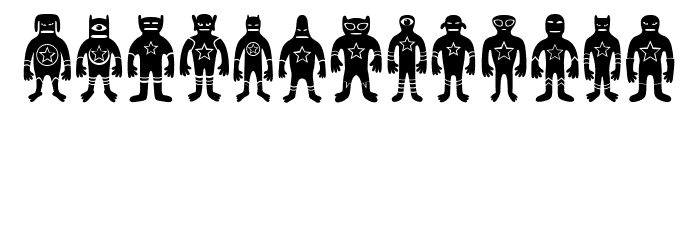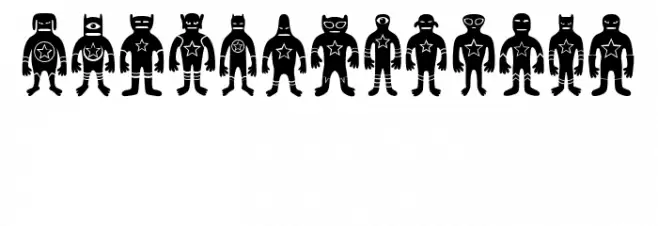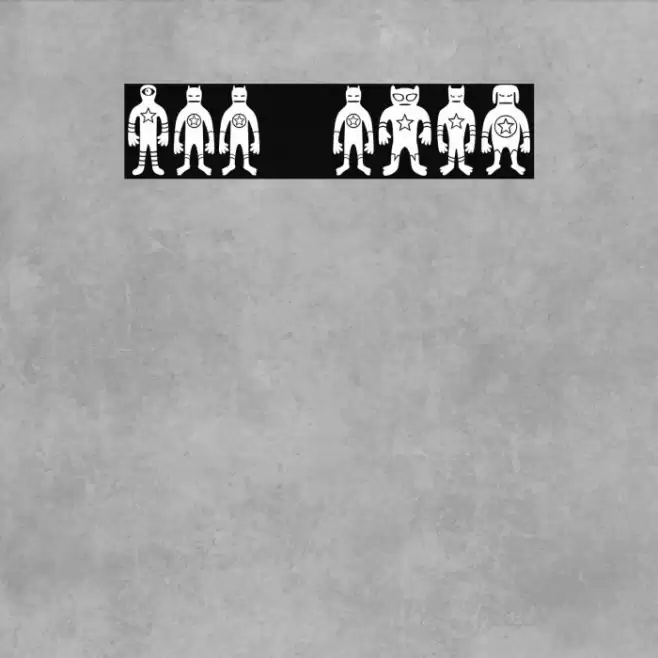
Heroez Regular Font
✎ Dingbats
| Caso de uso | Logos, Headlines, Posters |
| Proyectos propuestos | Ideal for comic books, children's posters, themed party invitations, and playful branding projects. |